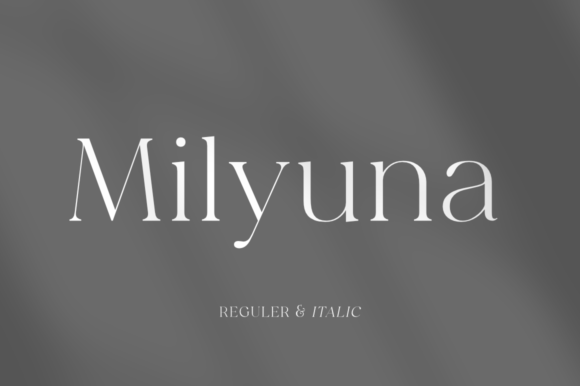
Creativefabrica Milyuna Font 2021
[Creativefabrica] Milyuna Font (2021)
Milyuna - это тонкий и элегантный шрифт с засечками.
Простой, но с сильным визуальным эффектом, этот шрифт мгновенно сделает ваше творение более привлекательным, чем любое другое.